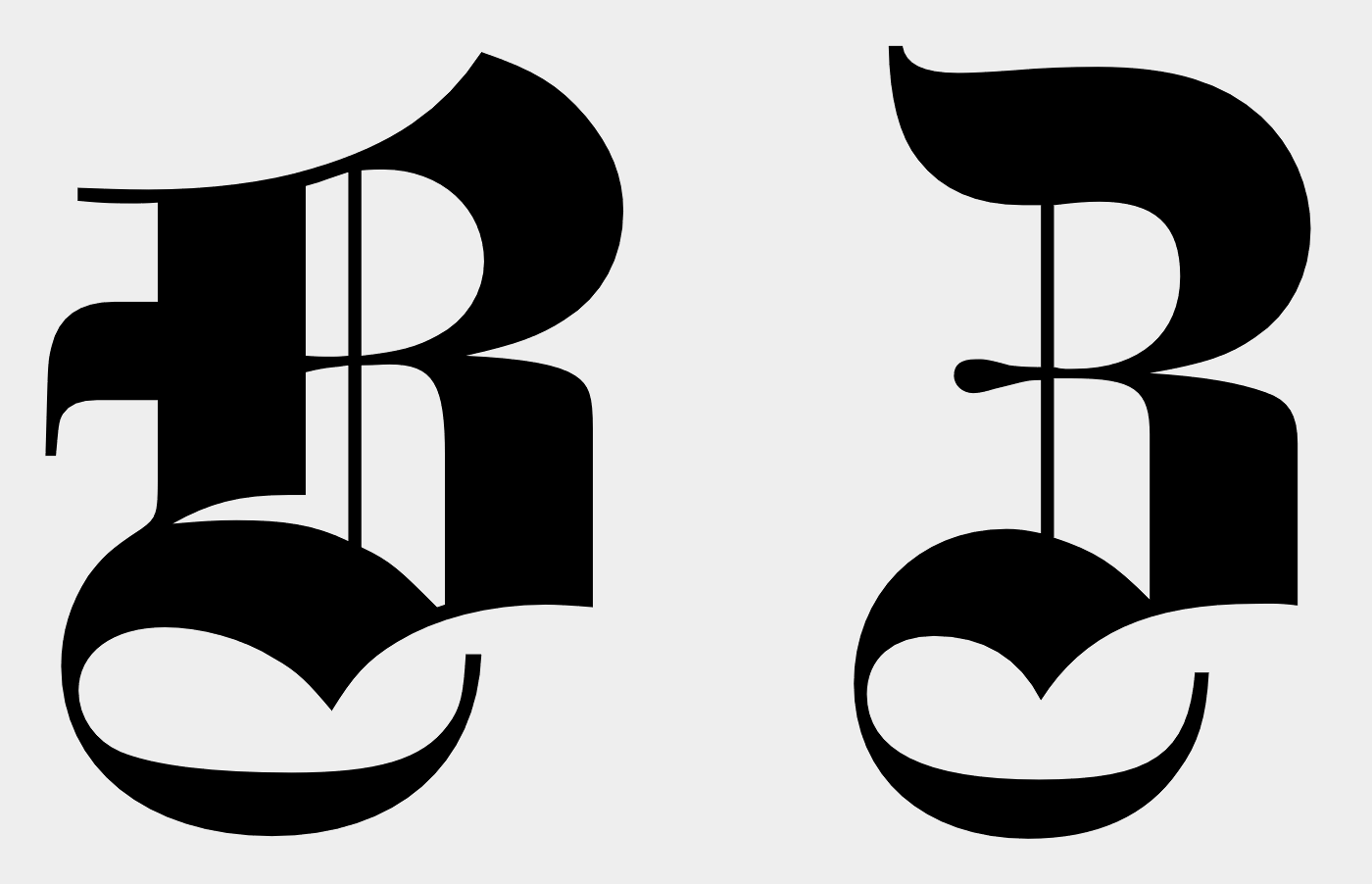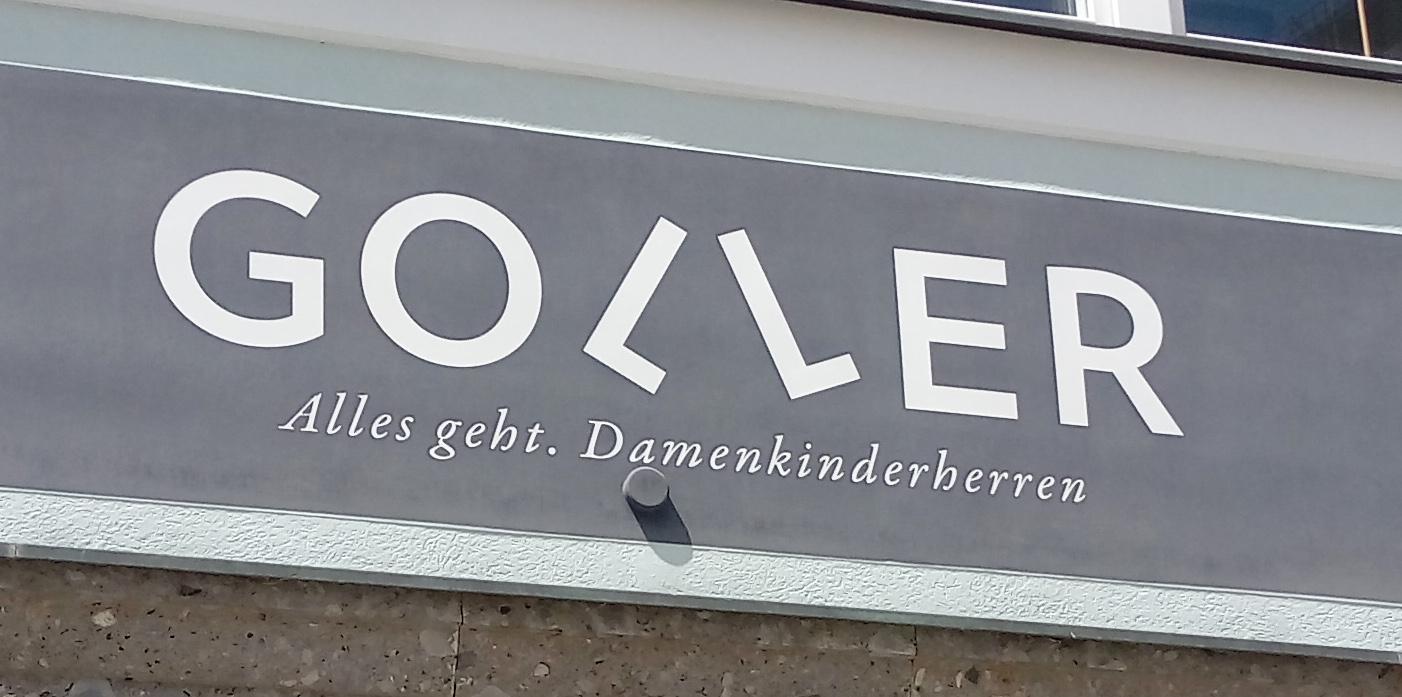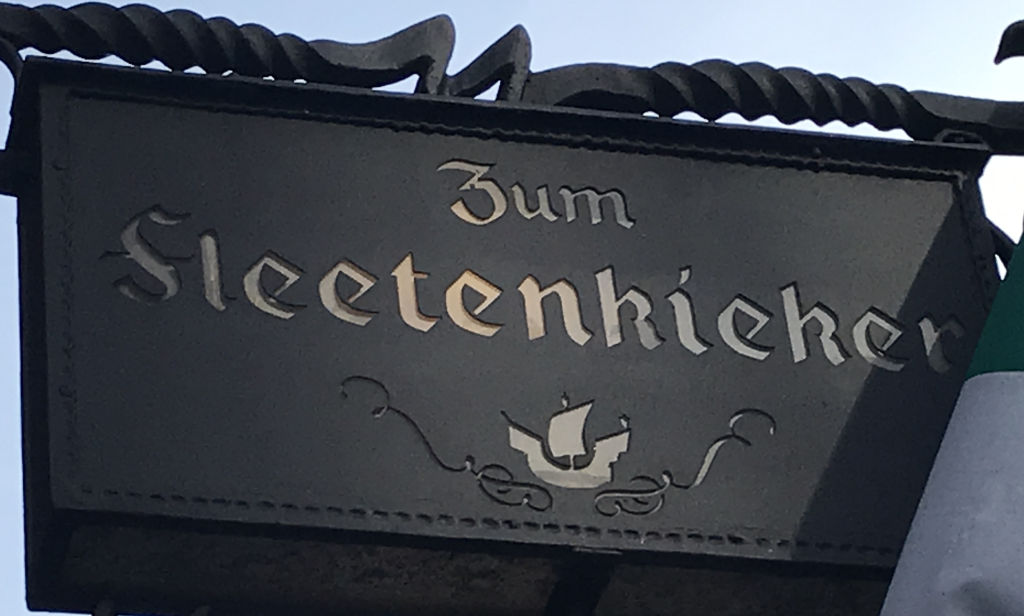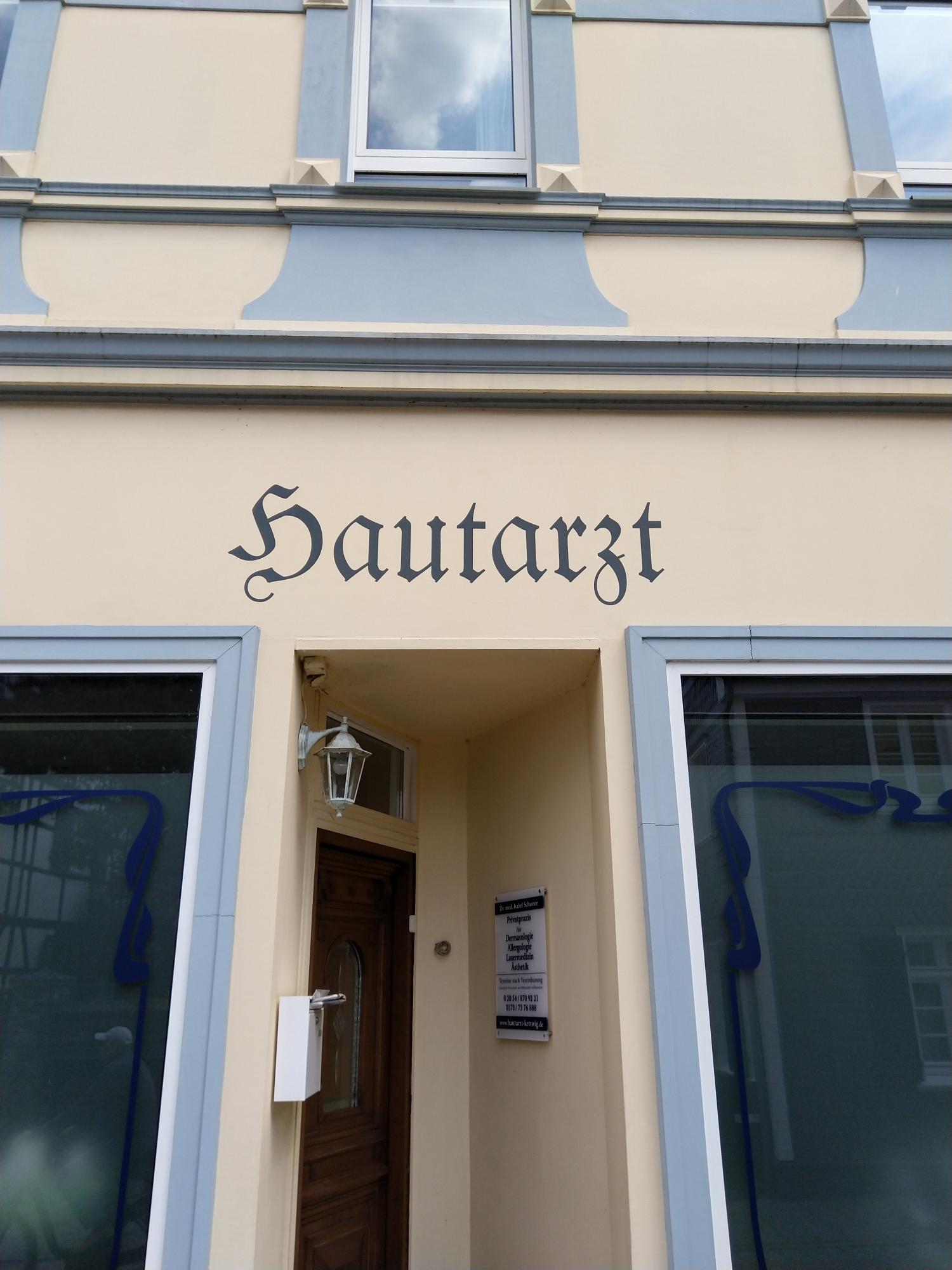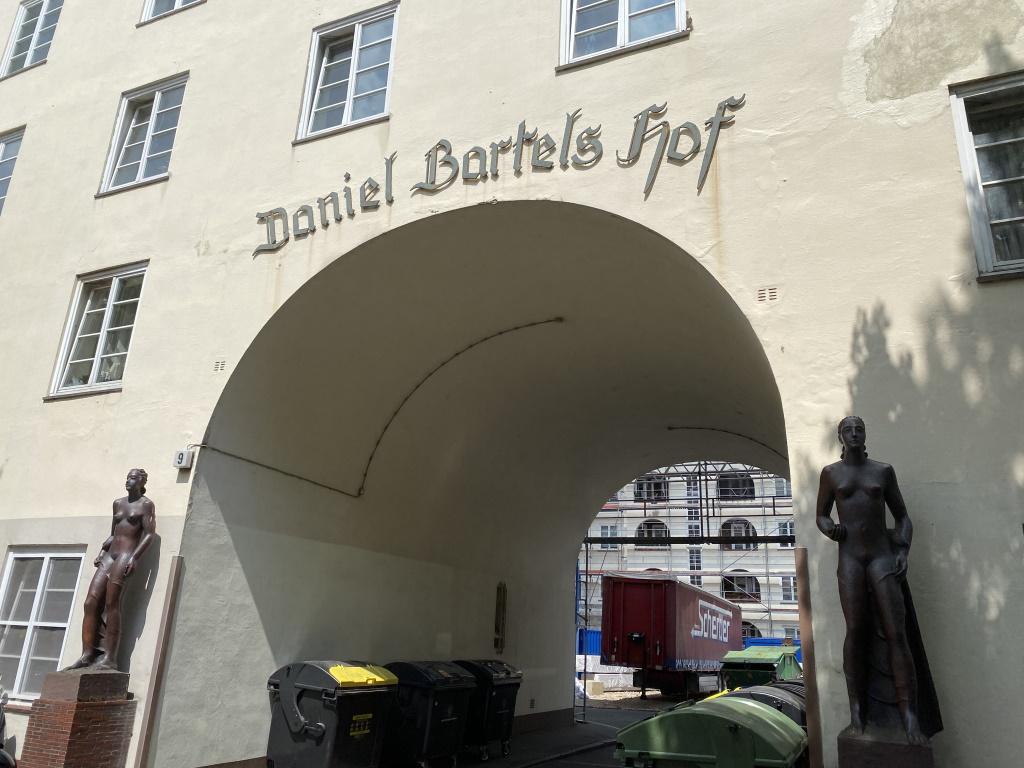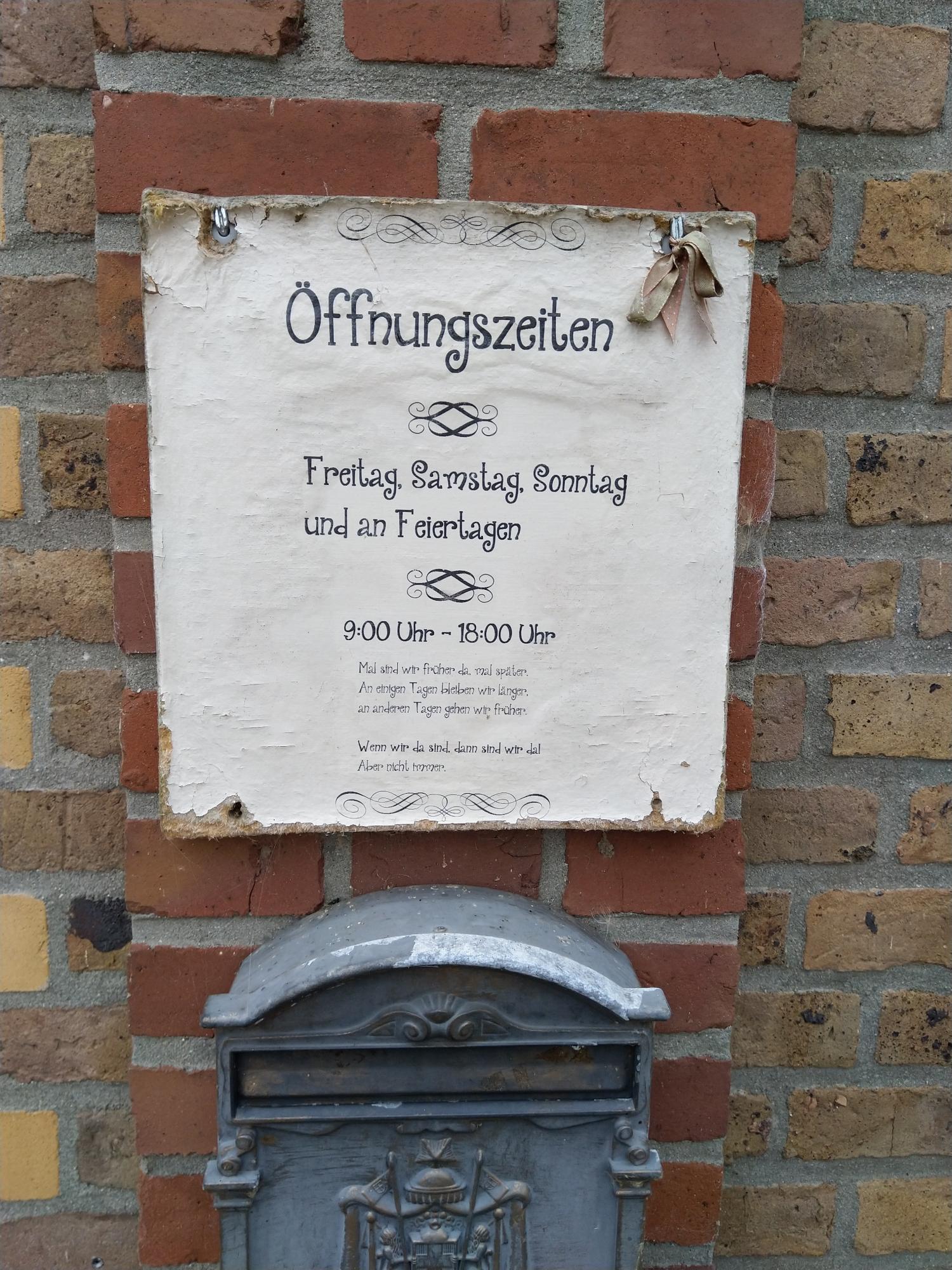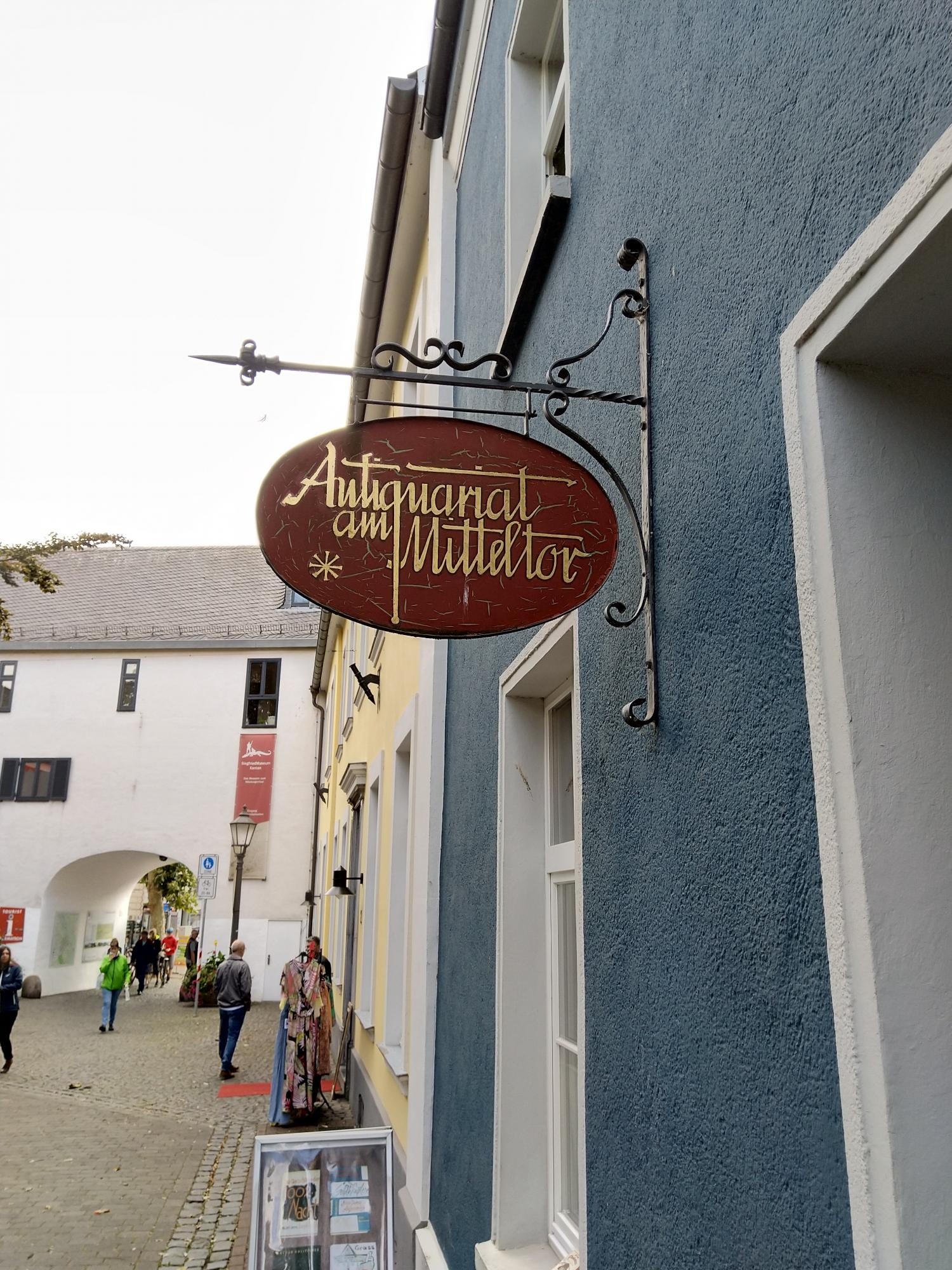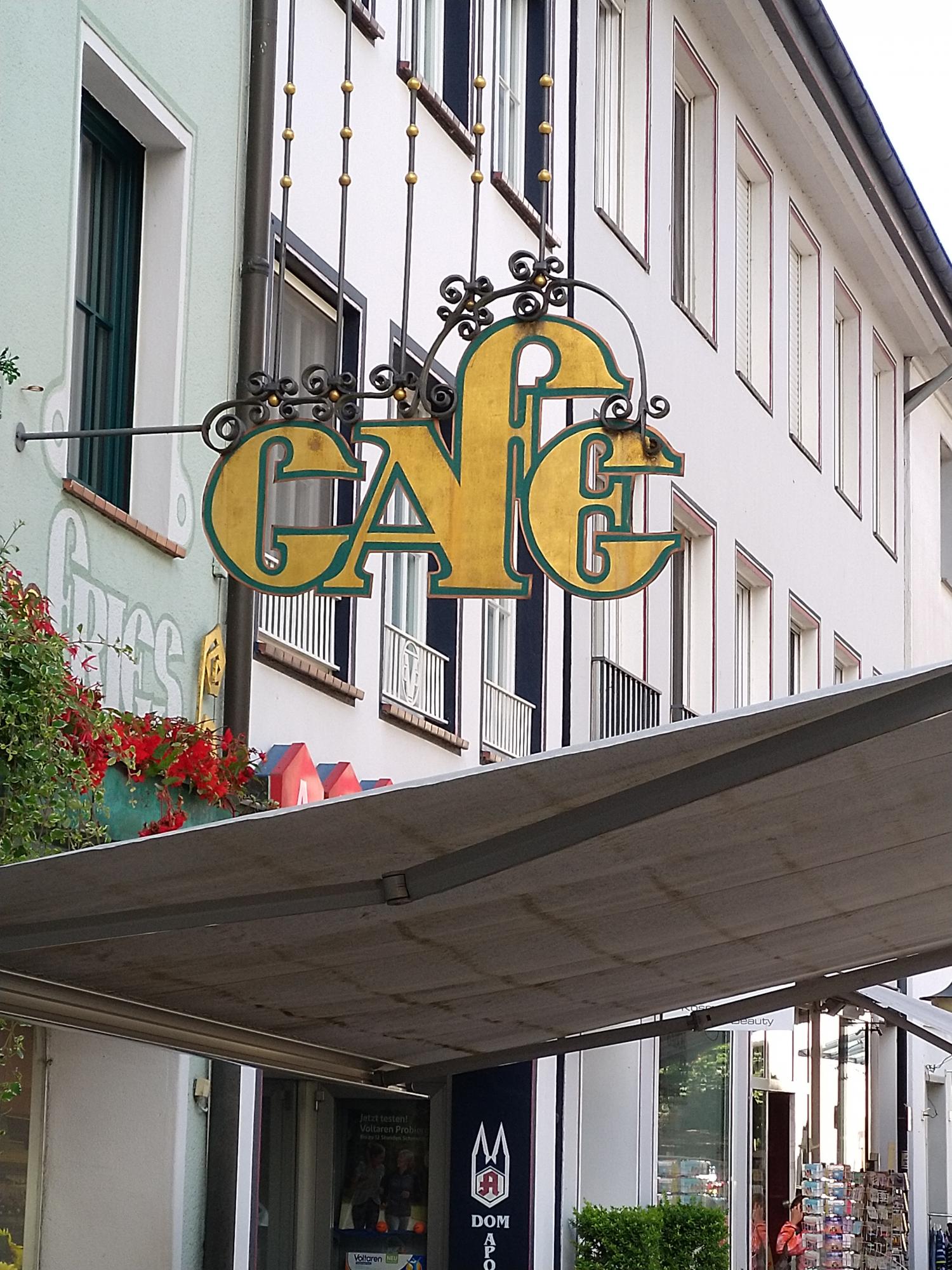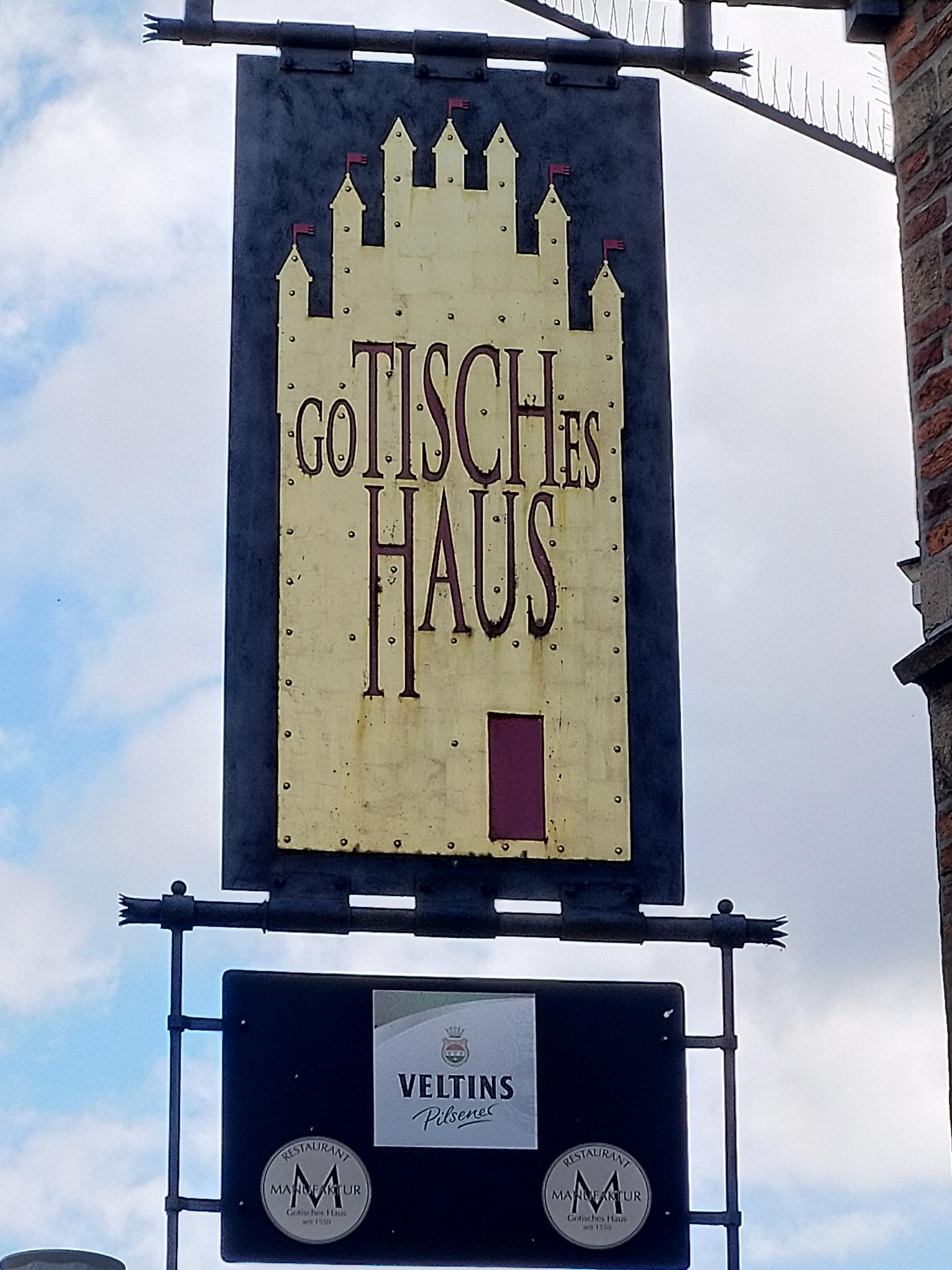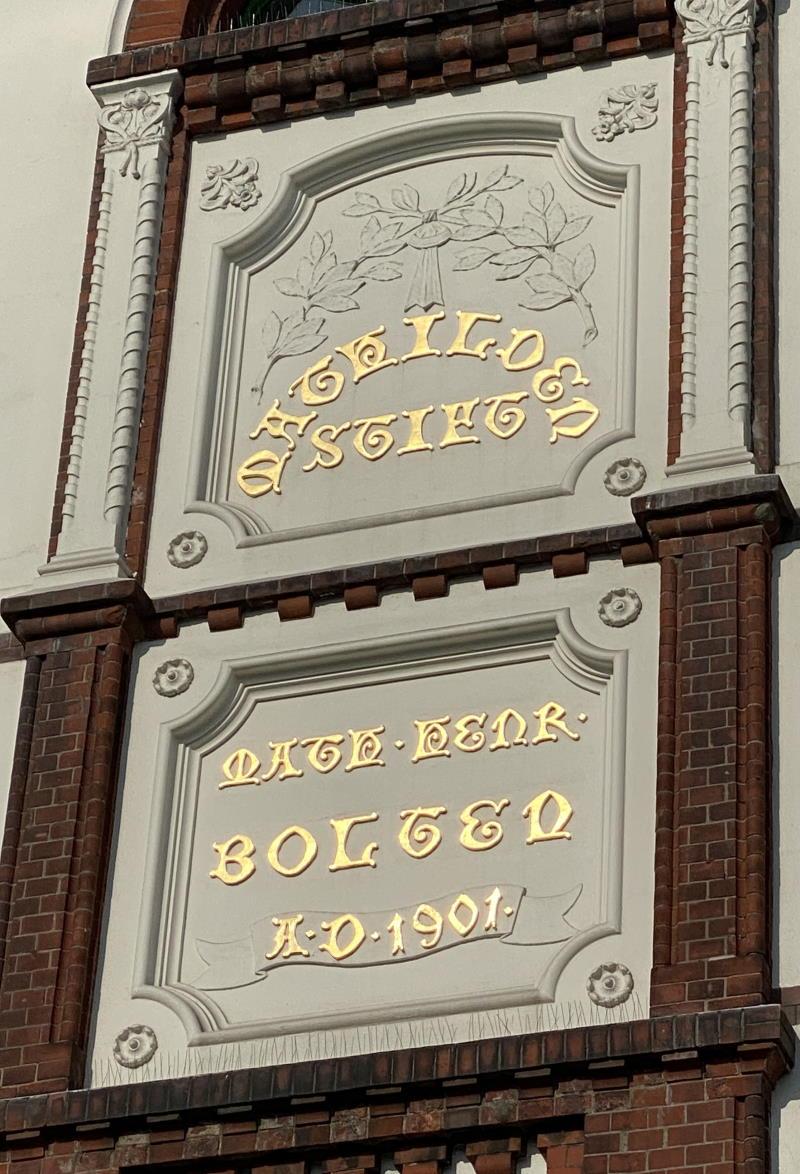
Typostreifzug durch die Stadt ...
Das wird vom falsch verwendeten Ampersand verwirrt worden sein gewesen.
Thorsten lange hast du aber nicht in Berlin gewohnt. ;-) Berliner Humor versteht nicht wirklich jeder, das gebe ich gern zu. Wenn man dort lebt und das bereits schon mehr als ein halbes Jahrhundert  ist das wohl anders. Die Sprüche von der BSR auf ihren Fahrzeugen versteht auch nicht jeder ;-) Übrigens steht es dir frei die Äpfel, um die es hier nicht wirklich ging, nach dem Kauf auch nackig zu machen (schälen) Mal zur Abwechslung nicht alles  zu ernst nehmen. ;-) Wörüber ich nur schmunzeln musste war, dass Jemand nur durch einen fehlenden Buchstaben einen völlig anderen Wortsinn geschaffen hat, was wiederum auch beweist wie schwer die deutsche Sprache auch sein kann..
---durch einen fehlenden Buchstaben den Wortsinn verändert---  Oder durch ein Satzzeichen den  Sinn quasi umkehren . " Der brave Mann  denkt an s i c h   s e l b s t   zuletzt". - !!! - Der brave Mann denkt an s i c h !  Selbst zuletzt.
Ich glaube, dass es wohl in jeder Sprache Möglichkeiten gibt, ein Wort, oder gar eine ganze Aussage völlig zu verändern, indem nur ein Buchstabe entfernt, hinzugefügt oder verändert wird.
Dazu braucht man keinen Buchstaben. Ein einziger Punkt genügt, um die Aussage eines  Satzes komplette zu verändern :  " Der brave Mann denkt an sich selbst zuletzt!"
" Der brave Mann denkt an sich . Selbst zuletzt!"  Mr.Austin
Muss auch kein Punkt sein, letztlich geht es mit jedem Satzzeichen. Ein Beispiel, mal, wie im Internet offensichtlich üblich geworden ohne Kommas:
Die AfD sagt die Linke ist schädlich für Deutschland
Und jetzt bitte ergänze die Komma(s) entsprechend deiner Sichtweise...
Und jetzt bitte ergänze  ...
Ja, schlimmer geht's  immer!
Das alljährliche Aufräumen der Mobiltelephone hat ein paar Fundstücke aus Spaziergängen des letzten Jahres ans digitale Tageslicht geholt:
Die Fette Gotisch hat ebenfalls so ein Z … links B, rechts Z.
Also mit Sachen wie MAASS kommt mein (immer brave geupdatetes deutsches Sprachzentrum) nun gar nicht zurecht. Ist das nun ein langer oder kurzer Vokal? MAASS oder MAASS? :-?
Ich vermute, dass es ein langer Vokal ist, der vor Ewigkeiten gedoppelt wurde, als noch keiner an ein Versal-Eszett dachte.
Dieser Streifzug ist schon eine Weile her, so um 1990 herum, Miami (South Miami Beach, glaube ich)miami90015.jpg.da56861386fb64e188b4695851cba51c.jpgmiami90013.jpg.b70eab9417fd2583605a699fadceb3f5.jpgmiami90012.jpg.9a996f15d8ab4b7a23f564da43eab868.jpg
Einzige USA-Reise – macht immer noch Spaß, mit dem neuen Scanner alte Dias einzuscannen.
Der Name steht da sicher nur drunter, weil man die andauernden Hinweise, dass man Tee-Maß doch anders schreibe, satt hatte.
Wobei das so natürlich überhaupt nicht hilft. Ist Herr Maß zu sprechen? Keine große Sache, ich wollte ihn nur darauf hinweisen, dass es jetzt auch ein ẞ für den Versalsatz gibt.
Und so ein »asiatisch-gebrochenes« ẞ wäre generell mal was! :biglove:
Die Tage beim Spazierengehen entdeckt, finde aber, dass ein paar Bindestriche das noch schöner gemacht hätten:
Oder man könnte es lesen als »Der Hof vom  Daniel Bartel« und würde sich darüber freuen, dass kein Apostroph den »Bartel« und das »s« zerschneidet. (Ich gebe aber zu, dass diese Lesart eher nicht gemeint gewesen sein dürfte.)
Udder uff kölsch: däm Daniel Bartel singe Höff.
Erst erschreckend spät in meinem Leben erfuhr ich, daß Xanten bis in die Gegenwart überdauert hat. "Es wuochs in Burgunden ein vil edel Magedin" oder so ähnlich...
So, mal wieder des Iphones Mediathek überflogen und gleich ein, zwei Fundstücke für Euch:
wenn an klebebuchstaben der zahn der zeit nagt wird aus einer gebrochenen schrift eine zerbröselte.
(schladming/steiermark)